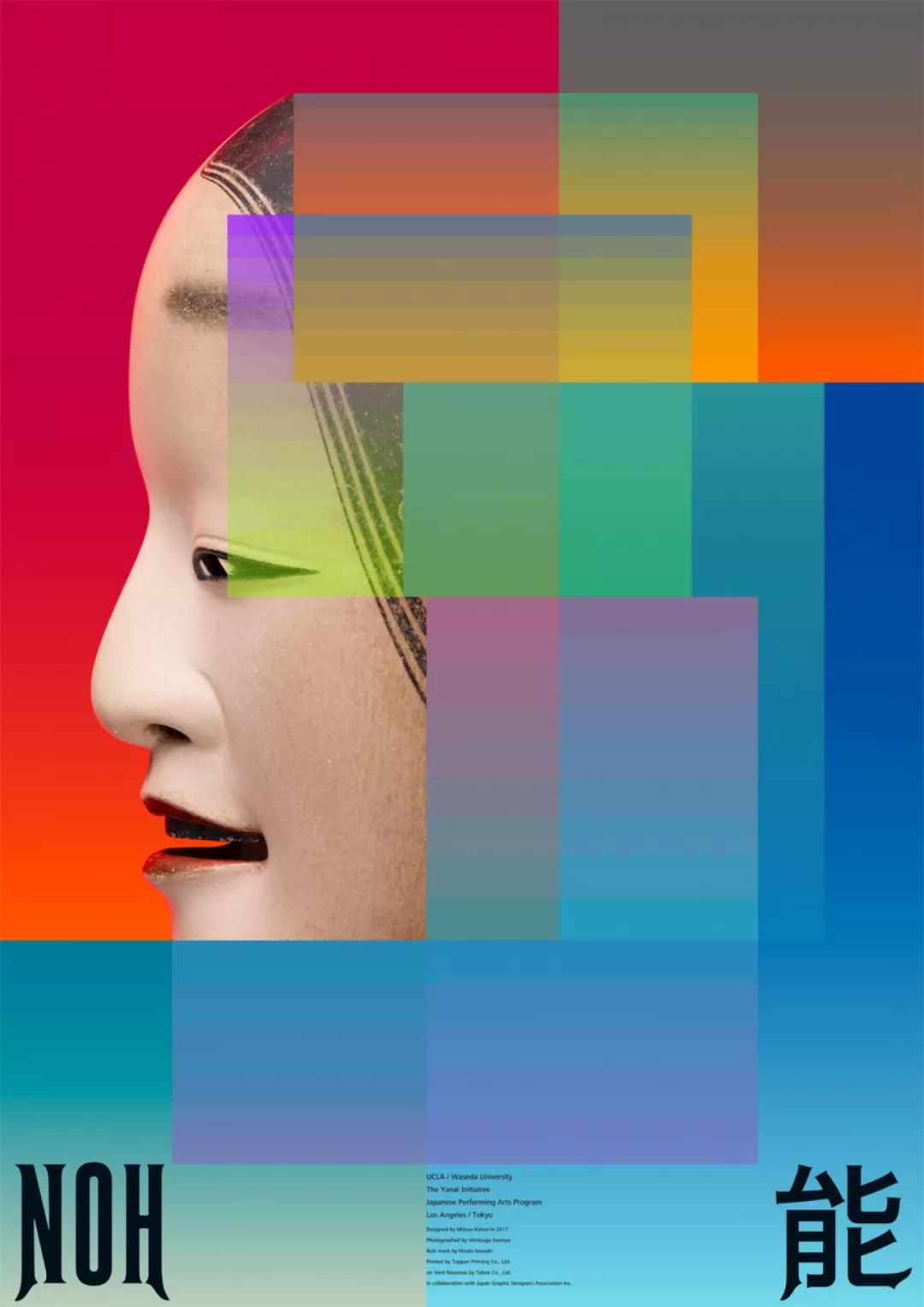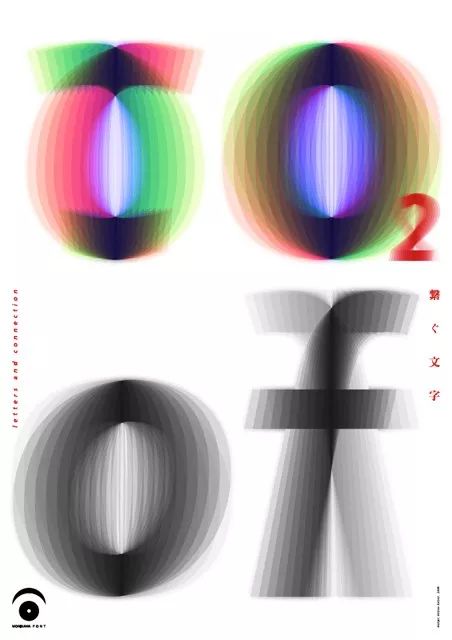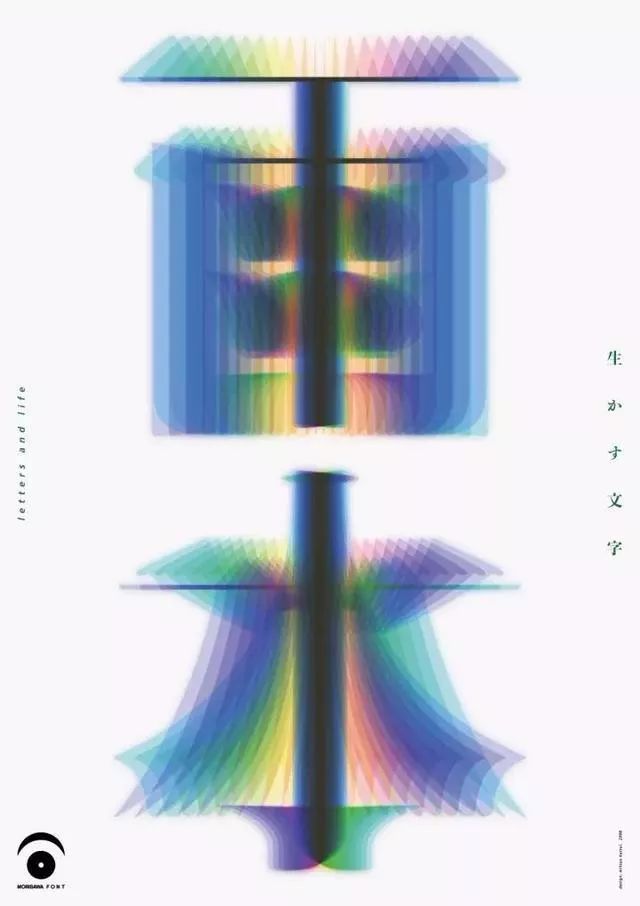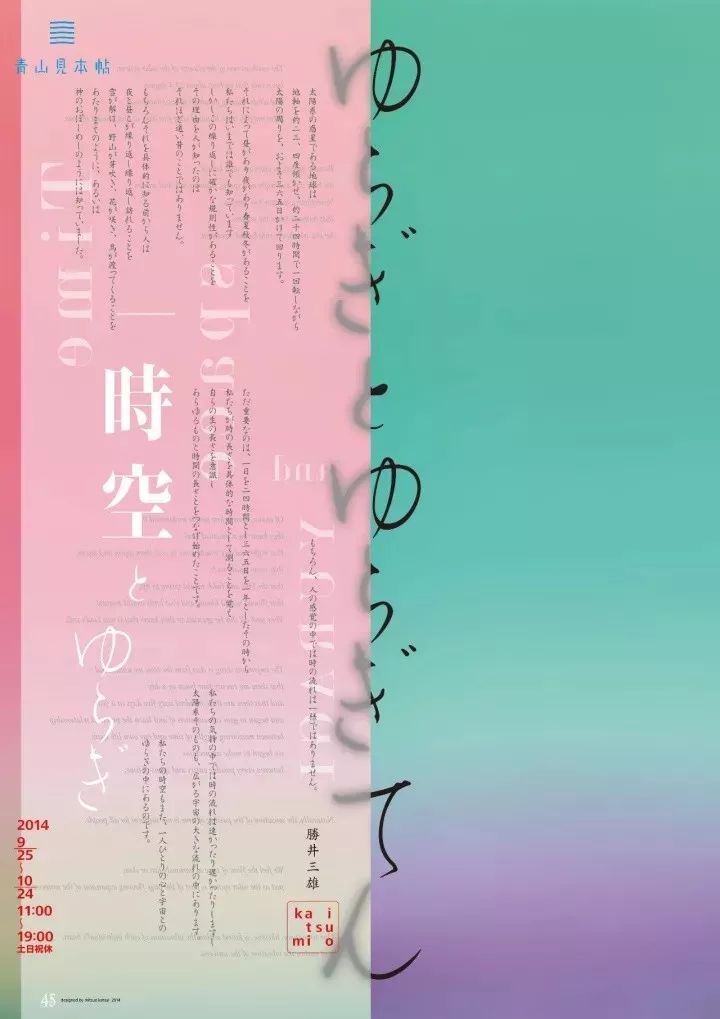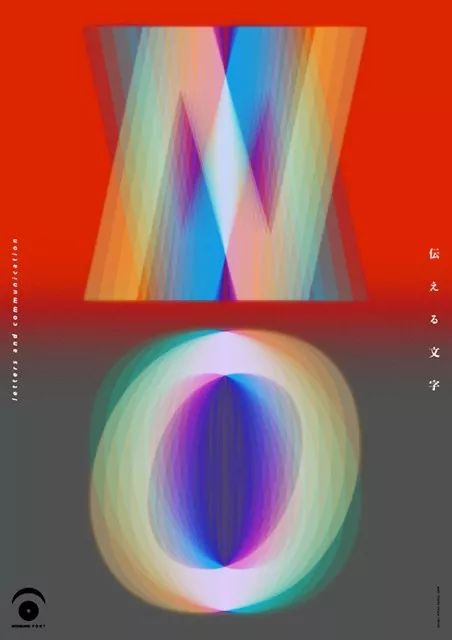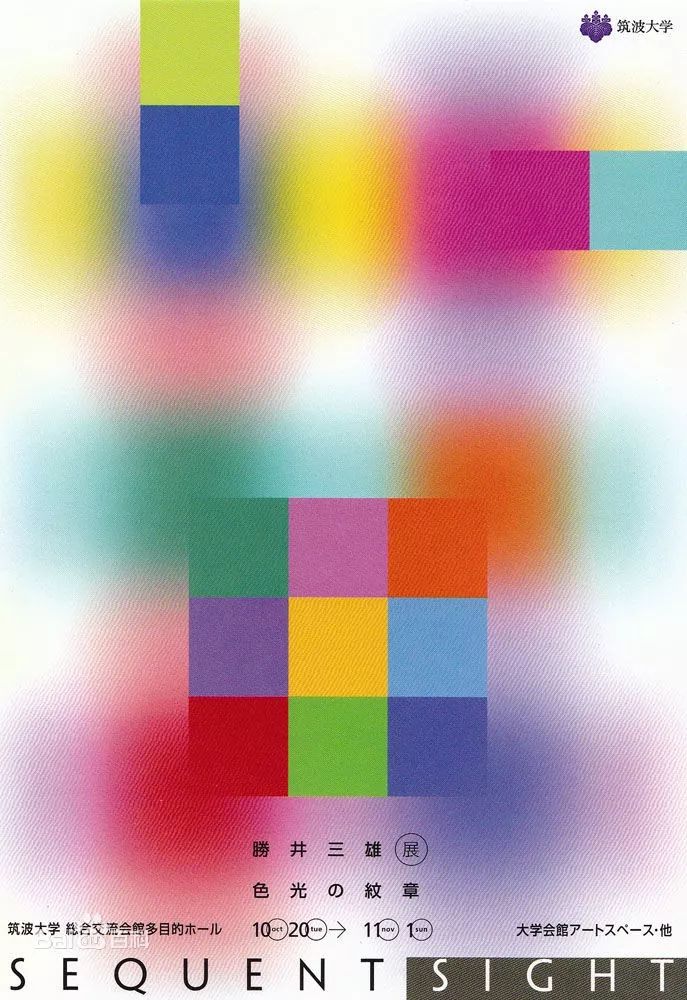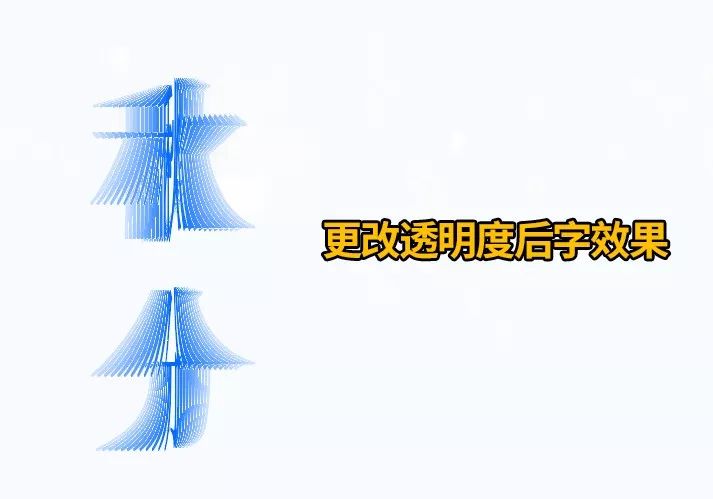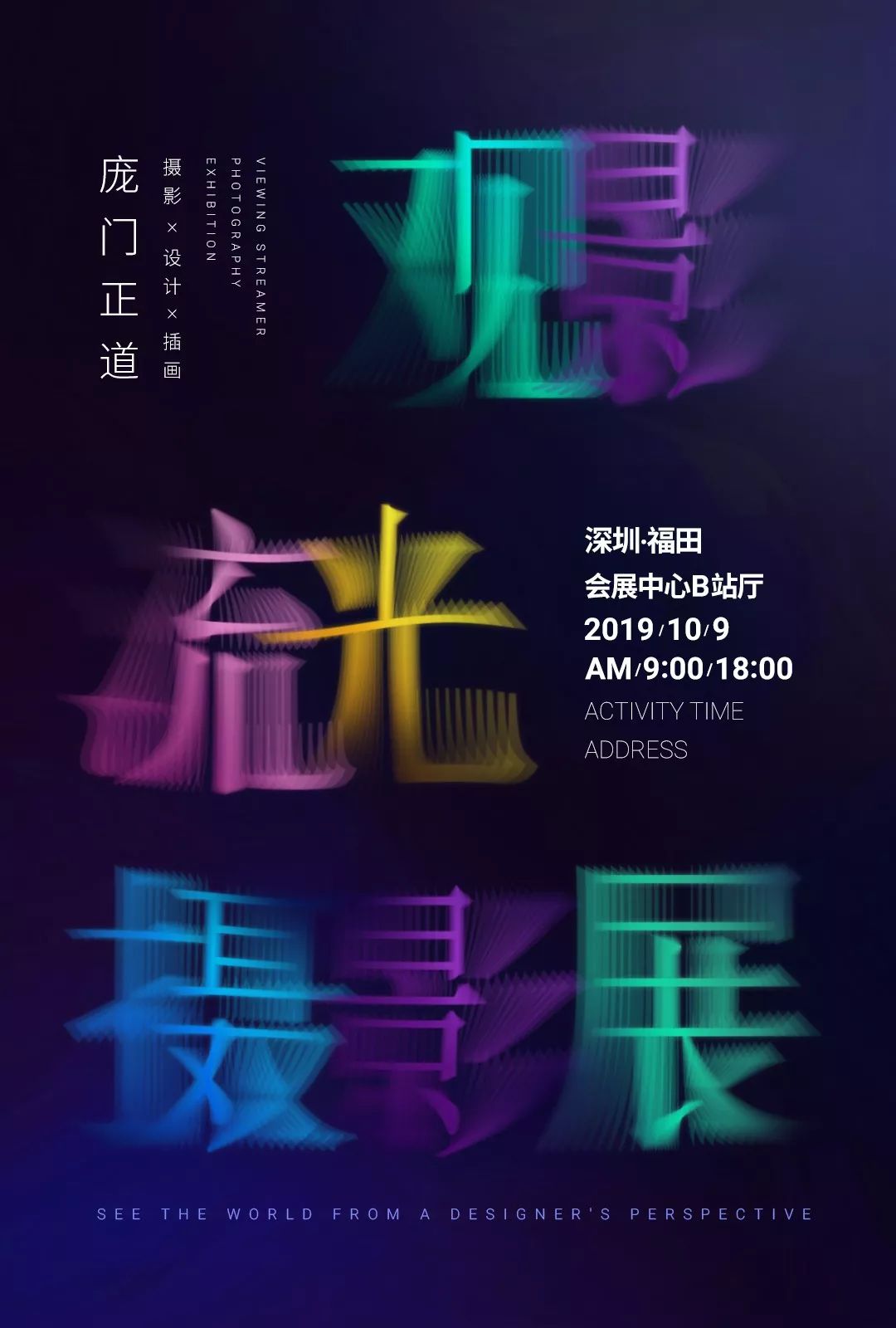
手把手做一张日本大师级海报!
今天教啥呢
先介绍位大师给大家
就是日本平面设计大师胜井三雄
不了解,没关系先看看大师作品
胜井大叔擅长用拼贴效果和独特错落结构
加上色彩缤纷变化手法呈现视觉作品
这些大师作品,
你就说帅不帅?
帅不帅?
今天就教大家用AI做胜井三雄式海报
例如下面这种大师代表式作品
首先在AI里打好字,选中文字单击右键在弹出里选中创建轮廓
选中字单击右键选择变换-缩放,弹出比例缩放对话框里选中不等比。水平数值10% 最后单击复制,这时画面就复制出一个水平缩放10%的字。
框选中两个字,执行混合选项功能快捷键CTRL+ALT+B,在双击混合工具会弹出混合选项,混合选项里设置指定步数,数值10确定。字混合效果完成。
接下来双击文字选中没有缩放的那层字,降低字透明度后字效果如下。
选中字执行对象菜单下的扩展,扩展选项里选中对象确定。在选中字单击右键执行取消编组,接下选中有字,给字加正片叠底效果。最后选中字执行CTRL+G对字进行编组。这时效果已经基本完成了。
选中文字右键在弹出框里选择变换-对称,弹出镜像对话框里选择垂直复制。更改下字的颜色胜井三雄式海报完成了。
溜号的同学注意下
还有更简单方法马上开讲
首先打好字降低字的透明度,单击鼠标右键选中创建轮廓。再选中字右键在弹出里选择变换-缩放,在弹出框里选中不等比,水平数值85%单击复制,这时画面就复制出一个水平缩放85%的字。
看似都和上一个方法一样 NONONO
这个方法更简单快捷马上见证奇迹
接下来只要重复一个动作就行,就是按CTRL+D这时画面会复制出一层字,不停按直到效果满意,是不是太更简单。
最后单击右键选择变换-对称,弹出镜像对话框里选择垂直复制。改下字的颜色,胜井三雄式海报又完成了。
只要跟着步骤一步步做
大师作品你也能拥有
又到案例时间
结合刚刚学到的两个方法
运用到实际案例中吧
来张高清大图看看